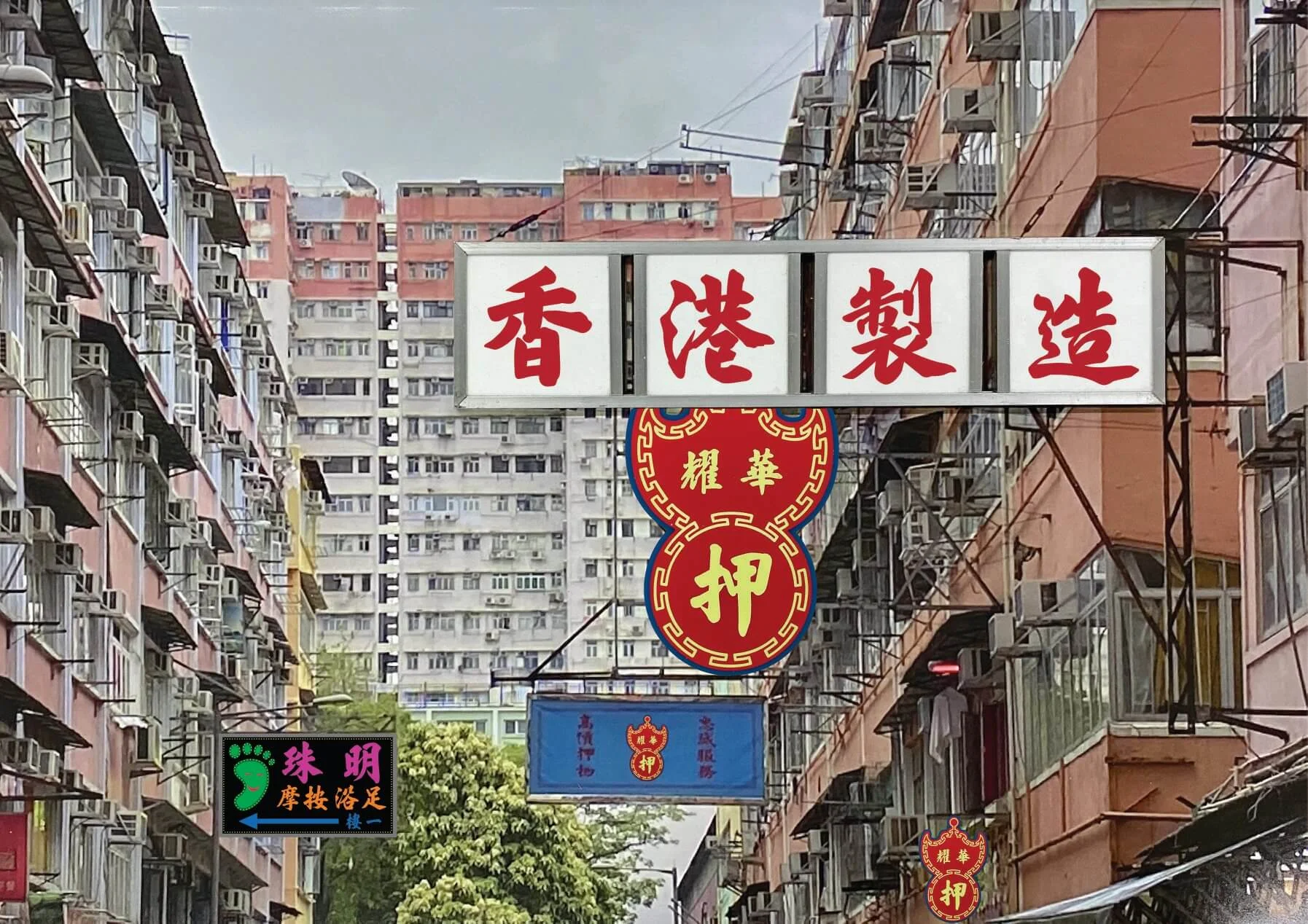
因着早前美國政府公告,下月底起香港生產的商品出口至美國時,原產地須標記為「中國」,網上泛起不少對「香港製造」的討論,有人覺得香港品牌將面臨衰落。但還有不少有心人繼續為「香港製造」默默耕耘,就如近期為「李漢港楷」眾籌的李健明。
曾經香港滿街盡是手寫的招牌,寫字匠李漢寫的一手字盡見於街頭巷尾。但隨着年月,街道的風光漸漸變了樣,這些招牌也逐一消逝。取而代之的是乏味的電腦字體,或過於耀眼喧囂的LED燈牌,少了從前來自手寫字的個人風格,及一份親和的感覺。
「李漢港楷」背後原來更埋藏着,由上一代人惺惺相惜,到新一代人傳承本土文化的故事。李健明父親李威,打從年輕從事招牌製作。當年造招牌要特意找寫字匠於原稿紙題字,然後依着字型切割成招牌字,李威在芸芸寫字師傅中結識李漢,因着合得來,而成為長期合作伙伴。在李漢快七十歲打算退休時,他因擔心李威往後沒有字體用,大筆揮毫依着字典寫下數千字相贈。繼承父親招牌製作公司的李健明,一早便想把如此獨特的真跡電腦化,奈何電腦配套不足。直至2016年,他自電台節目得知台灣有字體公司,能把字體手稿變化為電腦字,從此展開「造字」工程。他也透過導賞團、展覧,把這個在地的文化推得更廣。
「李漢字體復修計劃」期望製作一套七千多字的電腦字體,要撐起「香港製造」難以單靠一人之力,是以李健明發起眾籌計劃,希望至少籌上七十萬,以助完成這套屬於香港人的字。